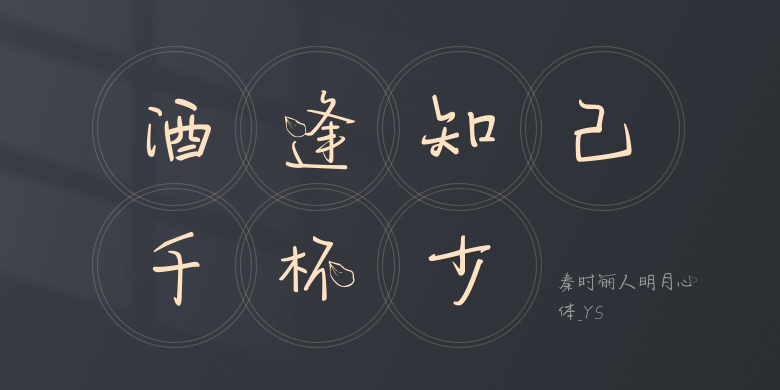
秦时丽人明月心体_YS
秦时丽人明月心体_YS,这款字体结构工整、笔画清晰,兼顾美观与易读性,适用于标题、正文、海报、包装、LOGO 等多种场景。字形优雅稳定,风格百搭耐看,适配日常排版与创意设计,让文字呈现更舒适、更具质感。秦时丽人明月心体_YS一笔一画,皆是细节,以均衡的比例、流畅的线条打造舒适视觉体验,字形端正大气,风格简约现代。无论是商业设计、品牌宣传还是日常排版,都能轻松驾驭,让文字更有格调与力量。秦时丽人明月心体_YS字体下载。